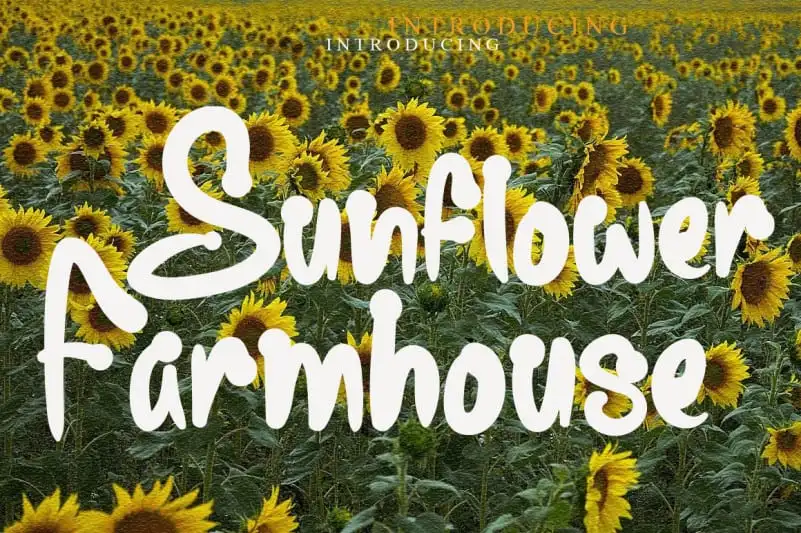
Sunflower Farmhouse Display Font – Download Grátis
A Sunflower Farmhouse Display Font é uma fonte escrita a mão que transmite relaxamento e frescura, perfeita para estilos modernos e fashionistas. Suas curvas suaves oferecem um visual leve e acolhedor ideal para branding de moda ou designs editoriais. Esta fonte é perfeita para quem busca um toque pessoal em seus projetos sem perder a elegância desejada. Com o seu uso, você certamente vai apreciar os resultados criativos que ela pode proporcionar. Seja na sua próxima peça editorial fashion ou no layout de uma campanha de moda, essa fonte será um brilho único e acolhedor para qualquer projeto.